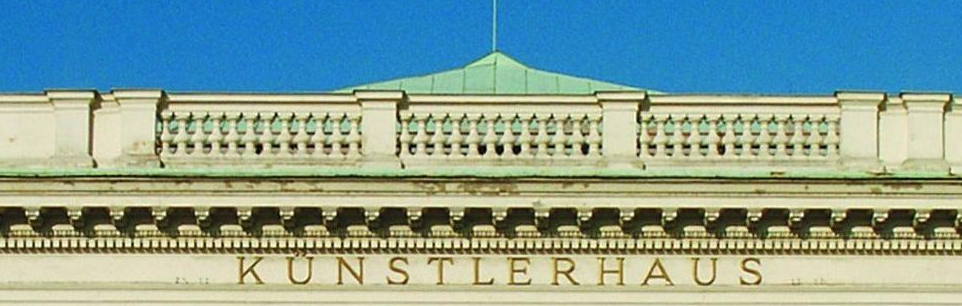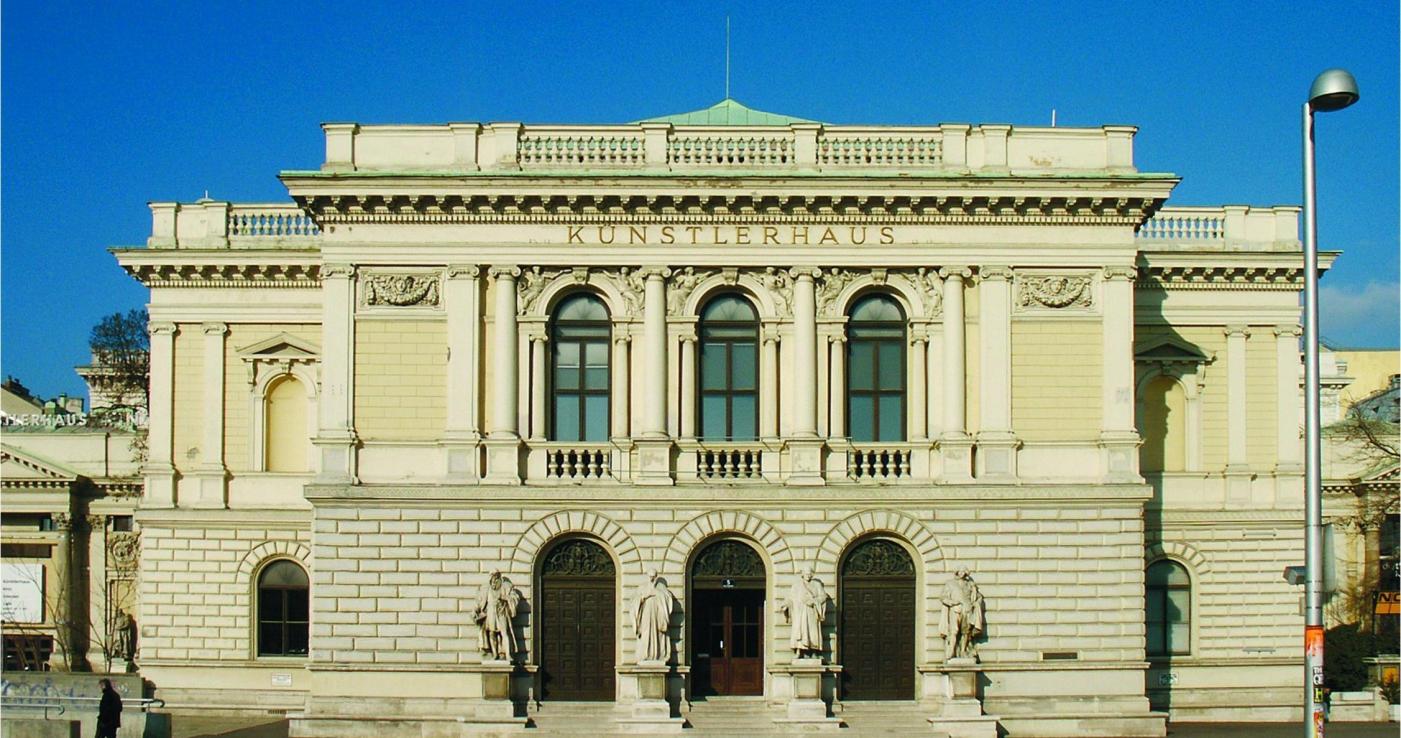
Künstlerhaus Wien - Schriftzug Fassade
ich bin auf der Suche nach dem Namen des Schriftzugs "Künstlerhaus", der in goldenen Buchstaben oben an der Fassade befestigt ist. Weiß zufällig jemand auch von wem der entworfen wurde?
Die Schrift wird so keinen Namen haben, da es 1865 noch nicht die Möglichkeiten in Bezug auf Schriften gab wie heute. Das wird jemand eigens gezeichnet und handwerklich erstellt haben. Ob es der Architekt August Weber selber war :-?
Es könnte aber auch sein, dass es sich hier um die CAT Kuenstlerhaus in spe handelt